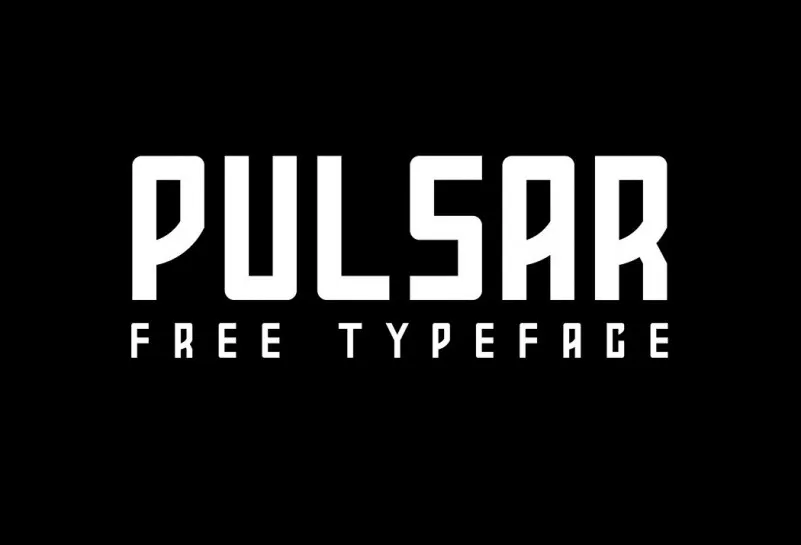
Agradecemos pela consulta ao Pulsar Typeface. Esta é uma fonte sans-serif com linhas contornadas que traz uma sensação de espírito, aventura e incrível alternância. Com suas linhas retas e marcantes, Pulsar oferece um toque atraente para qualquer projeto gráfico, seja em design editorial, publicidade ou website. Este é um tipo robusto e dinâmico, perfeito tanto para headlines quanto para subtítulos e textos de texto interativo. Hamilton é o designer por trás desta fonte, responsável pela sua forma arredondada e acentuada que adiciona uma sensação moderna e sofisticada. Não hesite em experimentar Pulsar; ela certamente irá complementar seu trabalho de design de uma maneira vibrante e inovadora.